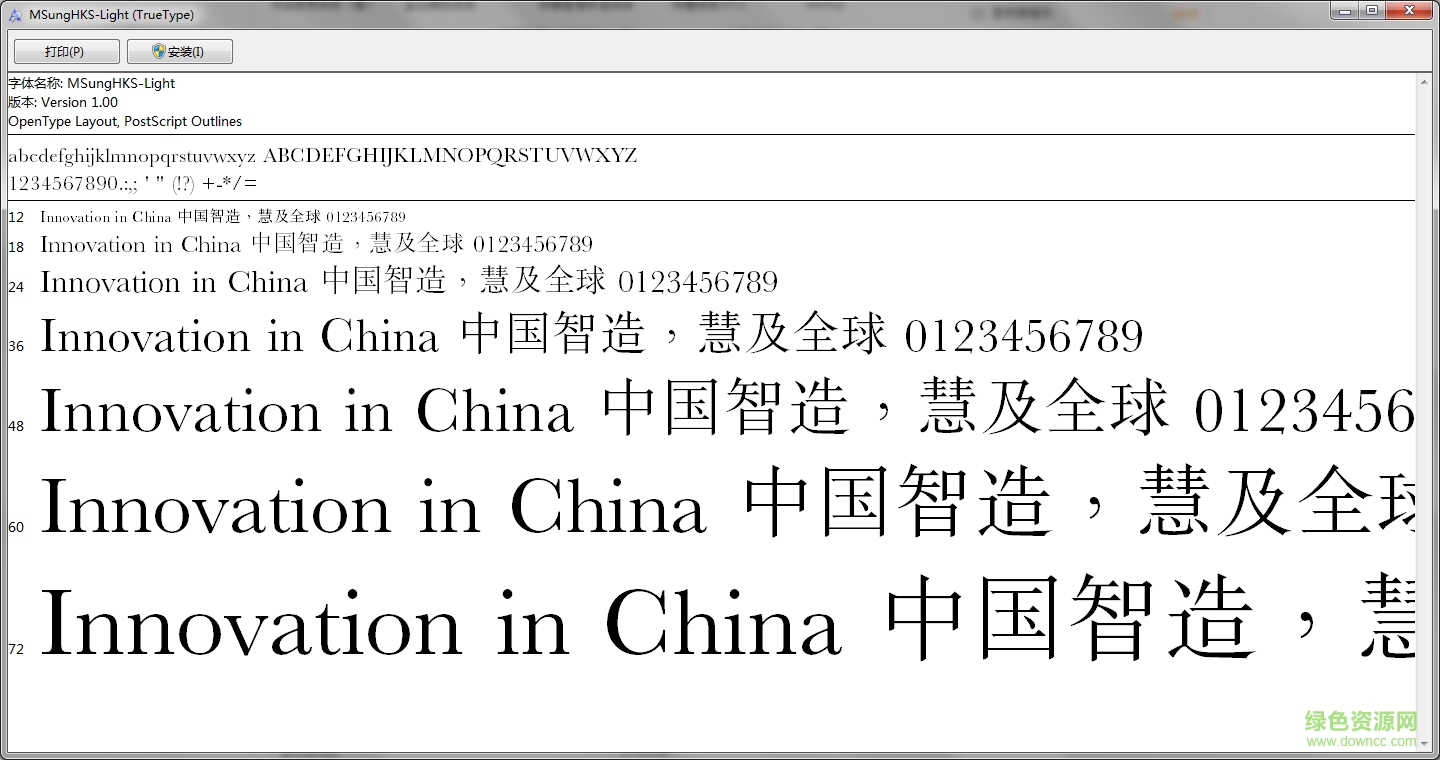
用于美工設(shè)計(jì)方面的字體,該字體端莊雄秀、神韻超逸、瘦勁清峻,看上去十分美觀,整體效果非常統(tǒng)一,且字庫(kù)完整,可以廣泛應(yīng)用于廣告設(shè)計(jì)、宣傳海報(bào)、ppt、影視制作以及內(nèi)容用字等領(lǐng)域,有需要的朋友可以免費(fèi)下載收藏。